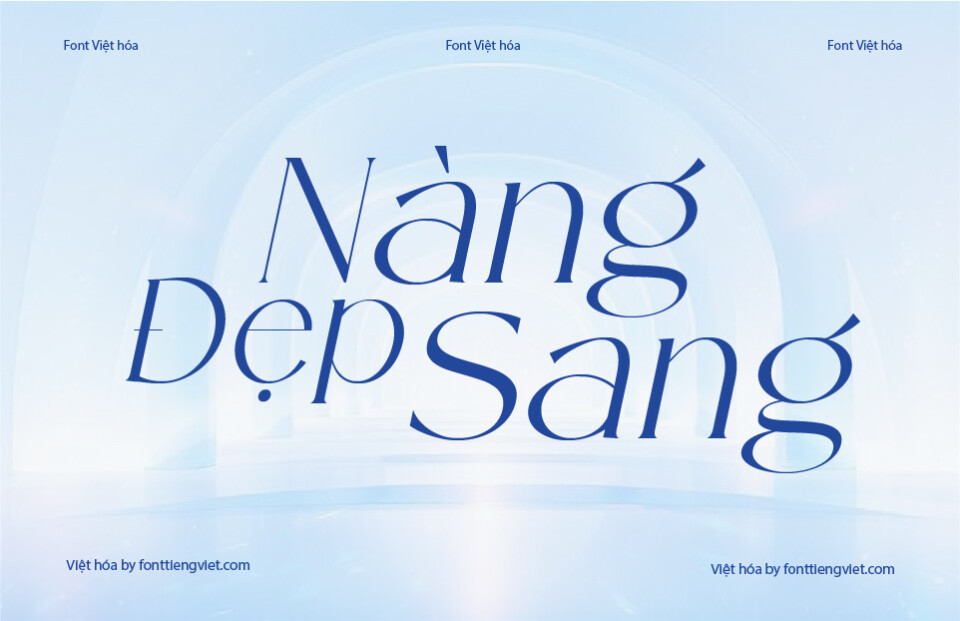
Font Việt hóa 1FTV VIP Sermo Italic
Giới thiệu về Font Việt hóa 1FTV VIP Sermo Italic
Trong thế giới thiết kế đồ họa hiện đại, việc tìm kiếm một bộ Font Miễn Phí chất lượng và hỗ trợ đầy đủ tiếng Việt luôn là ưu tiên hàng đầu của các bạn học sinh, sinh viên và thầy cô giáo. Font Việt hóa 1FTV VIP Sermo Italic nổi lên như một sự lựa chọn hoàn hảo nhờ sự kết hợp tinh tế giữa phong cách cổ điển và hơi thở đương đại. Đây là phiên bản nghiêng (Italic) nằm trong bộ sưu tập VIP được đội ngũ 1FTV chăm chút kỹ lưỡng về dấu câu, giúp các văn bản tiếng Việt trở nên chuyên nghiệp và hài hòa hơn bao giờ hết. Với những đường nét uyển chuyển, bộ phông chữ này không chỉ giúp nội dung dễ đọc mà còn tạo ra một dấu ấn cá nhân đậm nét cho người sử dụng.
Đặc điểm nổi bật của Font Việt hóa 1FTV VIP Sermo Italic
Phong cách thiết kế nghiêng đầy thanh lịch
Font Việt hóa 1FTV VIP Sermo Italic sở hữu những nét vẽ mềm mại với độ nghiêng vừa phải, tạo cảm giác chuyển động nhẹ nhàng và trang nhã. Khác với các kiểu chữ nghiêng thông thường, Sermo Italic giữ được cấu trúc chữ ổn định, không bị méo hình khi phóng to hay thu nhỏ. Điều này cực kỳ quan trọng khi các bạn áp dụng vào các tiêu đề slide thuyết trình hoặc làm thiệp mời trong các sự kiện nhà trường.
Tối ưu hóa khả năng hiển thị tiếng Việt
Điểm mạnh nhất của Font Việt hóa 1FTV VIP Sermo Italic chính là hệ thống dấu tiếng Việt được thiết kế lại một cách tỉ mỉ. Các dấu sắc, huyền, hỏi, ngã, nặng được đặt ở vị trí cân đối, không bị dính vào thân chữ hay gây rối mắt. Điều này giúp cho việc trình bày giáo án điện tử hoặc viết các bài báo tường trở nên rõ ràng, mạch lạc, đúng chuẩn phong cách giáo dục Việt Nam.
Ứng dụng thực tế của bộ font chữ trong học tập
Sáng tạo nội dung trên mạng xã hội
Hiện nay, việc tự thiết kế các ảnh trích dẫn (quotes) hay bìa video trên Canva, Photoshop là thói quen của nhiều bạn trẻ. Sử dụng Font Việt hóa 1FTV VIP Sermo Italic sẽ giúp các bức ảnh của bạn trông nghệ thuật và thu hút hơn. Kiểu chữ nghiêng này rất phù hợp để nhấn mạnh những câu nói hay, những thông điệp truyền cảm hứng cho bạn bè và cộng đồng.
Trang trí tài liệu và bài giảng điện tử
Đối với thầy cô giáo, việc làm mới giáo án bằng các phông chữ độc đáo như Font Việt hóa 1FTV VIP Sermo Italic sẽ giúp học sinh tập trung hơn vào bài giảng. Các phần ghi chú quan trọng hoặc các đề mục cần nhấn mạnh khi sử dụng định dạng Italic này sẽ tạo ra sự khác biệt thị giác rõ rệt, hỗ trợ quá trình tiếp thu kiến thức hiệu quả hơn.
Kết luận về giá trị của bộ font